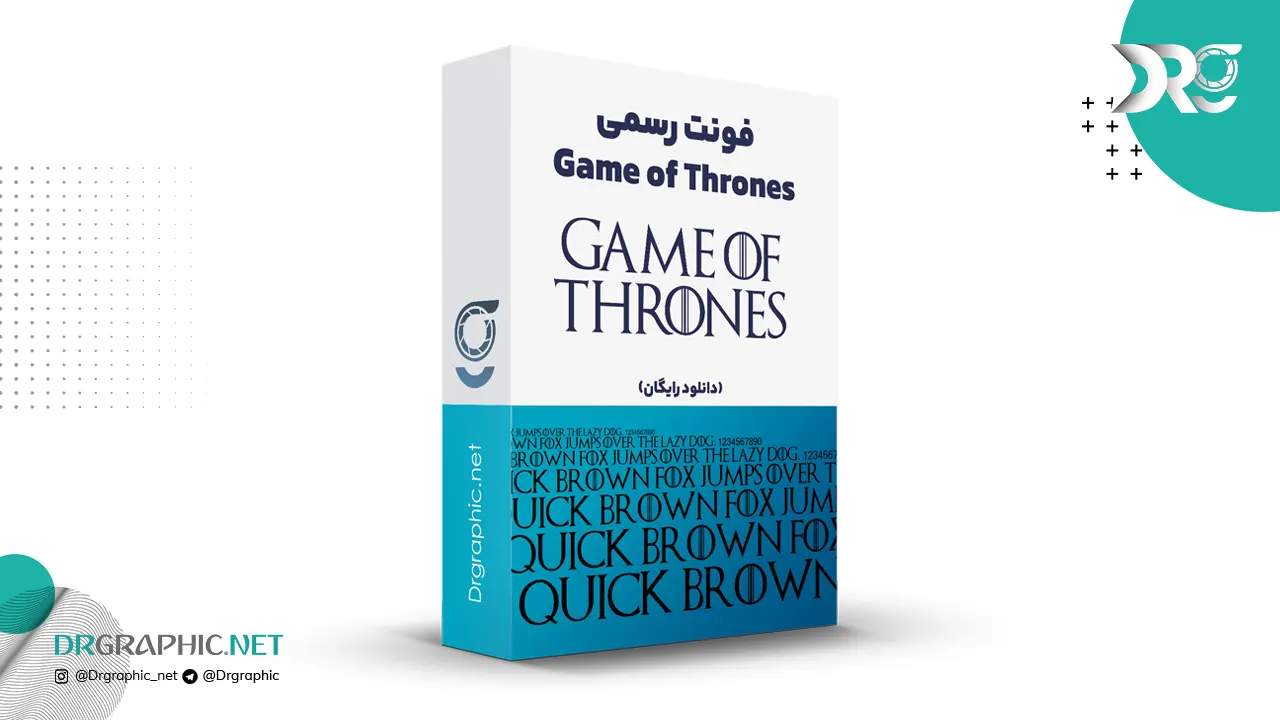
دانلود فونت انگلیسی گیم آف ترونز Game of Thrones
فونت Game of Thrones نام یک قلم لاتین شناخته شده و جذاب برای دوست‌داران سریال تلویزیونی بازی تاج و تخت است که طرفداران بسیاری در سراسر دنیا دارد. فونت به کار رفته در طراحی لوگوی این سریال تلویزیونی، جذابیت خاصی برای طرفداران آن دارد.
نمونه نوشته با این فونت: